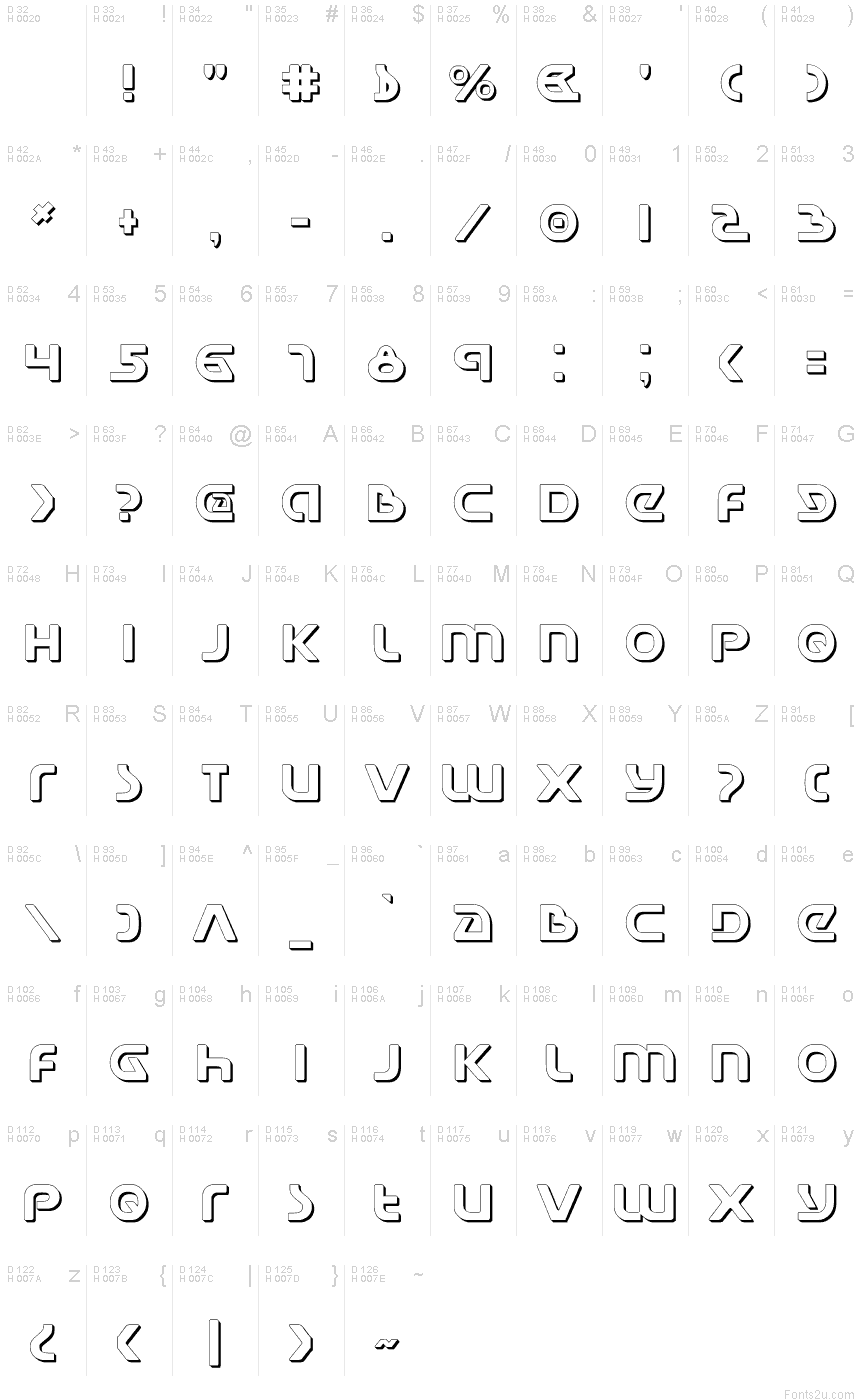
Universal Jack Shadow von Iconian Fonts ist eine kostenlose, futuristische Display-Schrift mit Schatteneffekt. Sie überzeugt durch elegante, abgerundete Großbuchstaben und versprüht den präzisen Techno-Vibe der frühen 2000er Jahre. Die Buchstaben wirken breit und konstruiert – mit weichen Ecken, markanten Einschnitten und einem harten, versetzten Schatten, der der Schrift Charakter verleiht, ohne überladen zu wirken.
Sie eignet sich ideal für Spiele-Logos, Sci-Fi-Poster, Album-Cover, Titelkarten und Branding für Tech-Events, bei denen es auf einen aufgeladenen, synthetischen Look ankommt. Da es sich um eine kostenlose Schrift handelt, ist sie zudem eine hervorragende Wahl für Kapitelüberschriften, Cover-Texte und Monogramme, da der Schatten selbst kurzen Wörtern eine enorme Präsenz verleiht.
Universal Jack Shadow
Dan Zadorozny